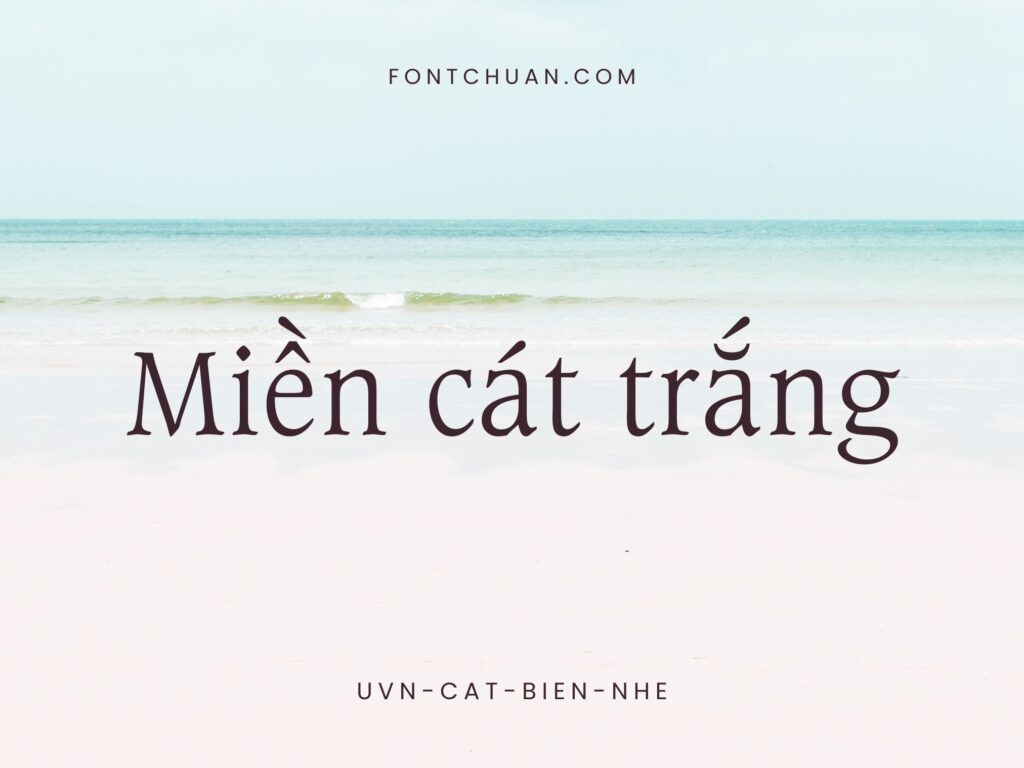
Font UVN Cat Bien Nhe Việt Hóa
UVN Cát Biển Nhẹ là phiên bản thanh thoát hơn của bộ font UVN Cát Biển nổi tiếng, được thiết kế với đường nét mảnh mai hơn nhưng vẫn giữ trọn vẻ duyên dáng và hiện đại. Lấy cảm hứng từ những con sóng dịu êm và bầu không khí nhẹ nhàng của vùng biển, font mang lại cảm giác mềm mại, gần gũi và rất dễ kết hợp trong nhiều phong cách thiết kế. Font này được thành viên Font Chuẩn sưu tầm và chọn lọc nhằm đáp ứng nhu cầu đa dạng của nhà thiết kế, từ in ấn đến thiết kế truyền thông và nhận diện thương hiệu.
Với cấu trúc chữ nhẹ, khoảng cách hợp lý, và các đường nét bo cong tinh tế, UVN Cát Biển Nhẹ dễ đọc, tạo cảm giác thoáng đãng, đặc biệt phù hợp với các thiết kế yêu cầu sự nhẹ nhàng, nữ tính hoặc mang yếu tố thiên nhiên. Font có thể ứng dụng tốt trong các poster, thiệp mời, thiết kế mùa hè hoặc các ấn phẩm quảng cáo du lịch. Các ngành nghề phù hợp bao gồm quảng cáo, giáo dục, công nghệ, bất động sản và ẩm thực. Ngoài ra, font này cũng rất lý tưởng cho các sự kiện như lễ hội, Tết, Trung thu, Valentine hoặc sinh nhật.